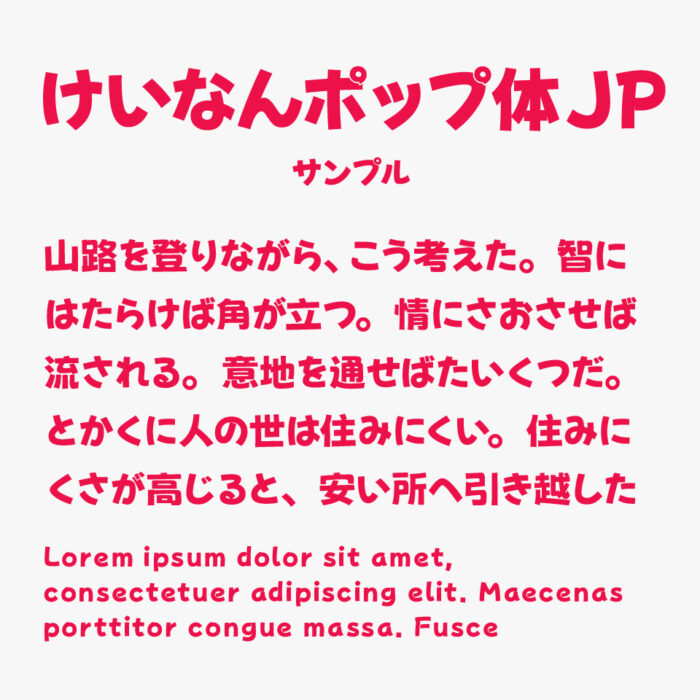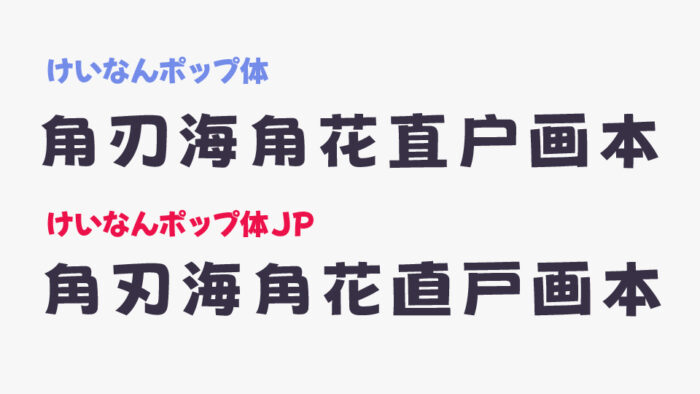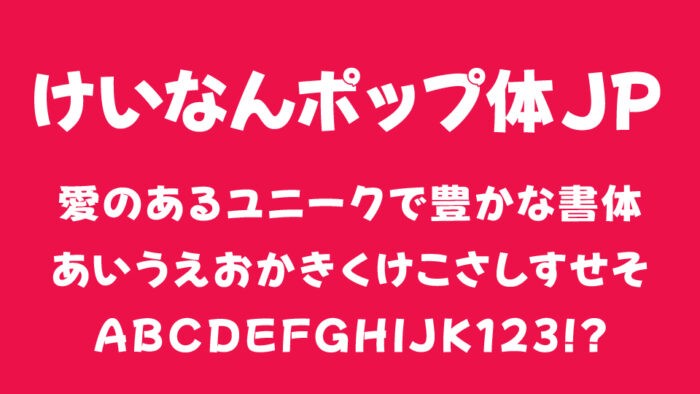
けいなんポップ体JPフォントは、「けいなんポップ体」フォントの一部の漢字が調整されたポップ体フォントです。
けいなんポップ体フォントの漢字は、中国語用フォント「荆南波波黑」を使用されていたため、日本語の標準字形と異なるものがありましたが、それらの文字が調整されています。
比較するとわかりやすいですが、一部の漢字が日本語漢字とは少し異なりますが、けいなんポップ体JPフォントではJIS第1水準漢字を中心に日本語仕様に字形が調整されています。